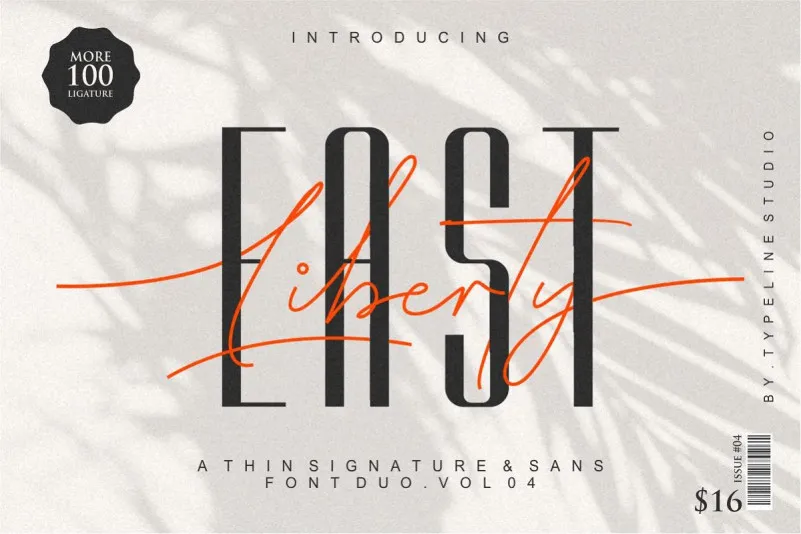
East Liberty Font Duo – Fonte Grátis
East Liberty Font Duo
Introduzimos East Liberty Thin Signature & Sans, uma fonte premium projetada pela typeline studio que agora está disponível de forma gratuita para download. Este é um duplo entre um script moderno e uma sans-serif condensada, perfeito para criar logomarcas, camisetas fotográficas, marca d’água da beleza, capas de revistas, conteúdo de revistas, citações e muito mais. Este novo conjunto está equipado com dois estilos: Thin Signature e Sans serif. O Thin Signature é um script moderno que traz uma sensação elegante à sua identidade visual, enquanto o sans-serif condensado adiciona um toque minimalista. Ambos têm a capacidade de criar designs multifacetados, tornando-os ideais para variadas aplicações e tendências atuais. A typeline studio é conhecida por suas fontes limpas e elegantes, criadas com uma atenção ao detalhe que resultam em resultados impactantes. Este duplo é perfeito tanto para aqueles buscando um estilo clássico quanto para os que estão procurando algo mais moderno. Ele atende às necessidades de diversos projetos desde logos até citações e conteúdo editorial, garantindo sempre a qualidade e o bom design esperados na typeline studio. Descubra por si mesmo como estas fontes podem transformar seus projetos digitais em verdadeiros hits. Com East Liberty Thin Signature & Sans você terá tudo o que precisa para criar um design único e profissionalmente elaborado, sem custo adicional.